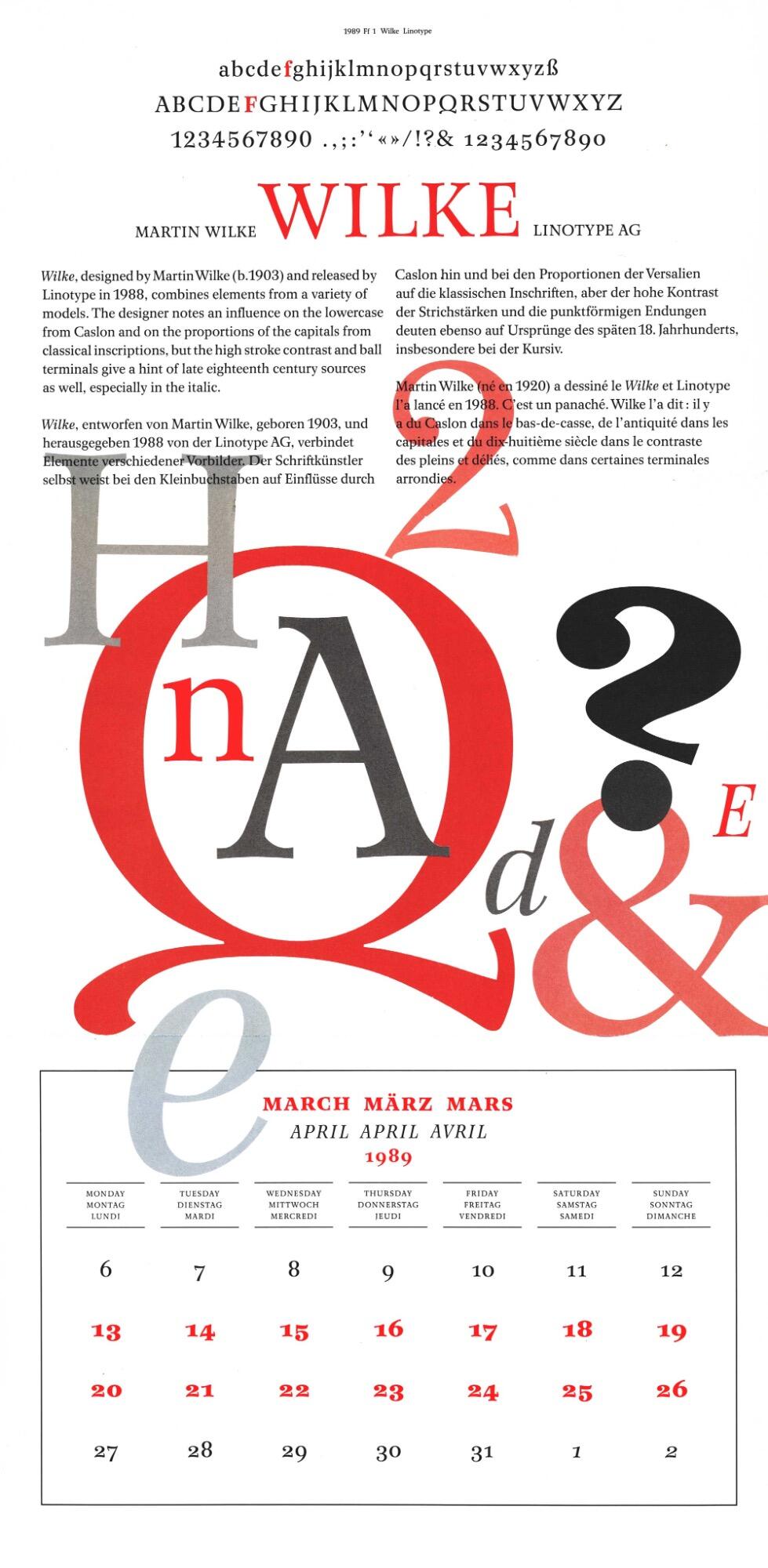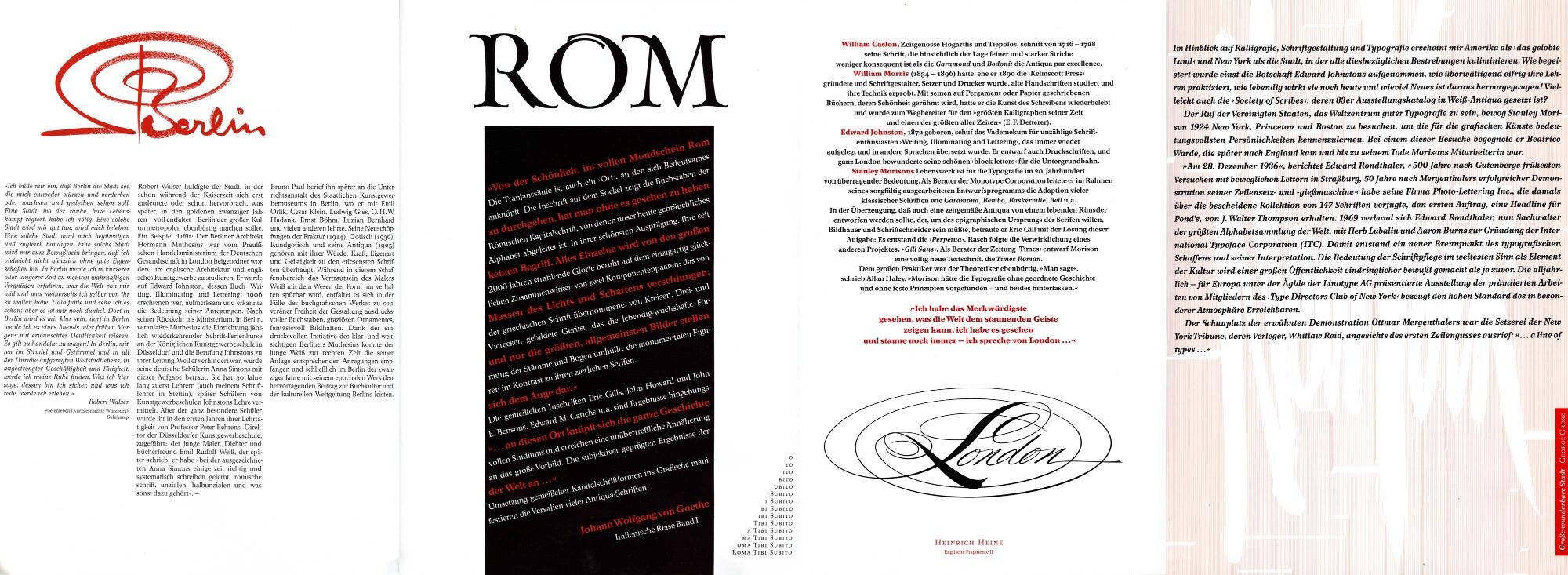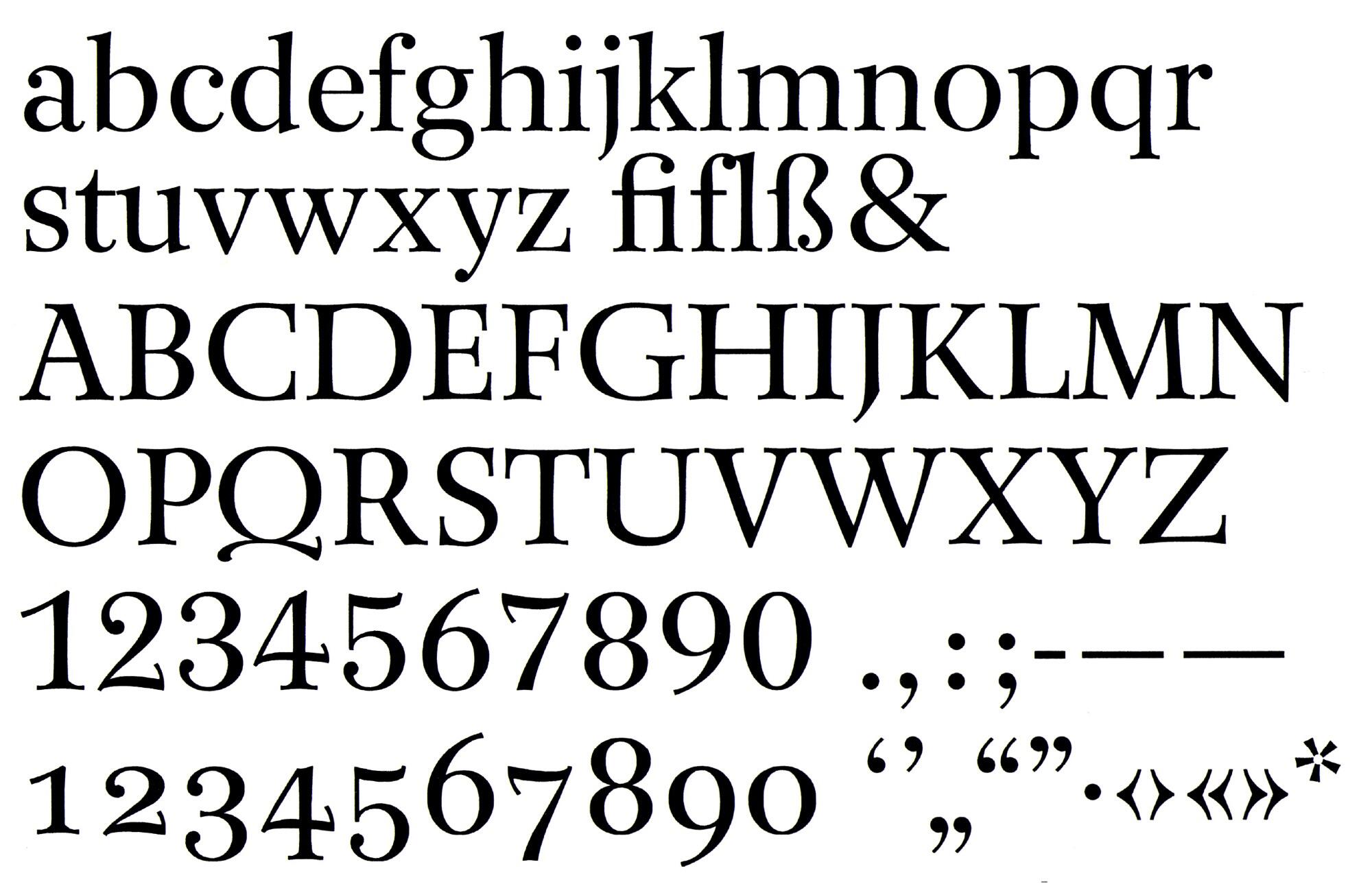
Die Wilke ist eine nach ihrem Gestalter Martin Wilke benannte Barock-Antiqua, 1988 herausgegeben von Linotype für den Fotosatz. In drei Schnitten mit Kursiven veröffentlicht, benannte Wilke die frührömische Capitalis Quadrata, die Kalligraphie des Book of Kells, Schriften Jan van de Veldes und die Caslon-Antiqua als Einflüsse.
Bei der Erstellung seiner letzten veröffentlichten Schrift setzte Martin Wilke auf organische Elemente für eine ›Schrift ohne Kühle und Strenge‹. Die Wilke hat eine leichte Vorwärtsneigung, alle Konturen sind leicht geschwungen, und außer bei den Querstrichen von A, f und t enthält sie keine geraden Linien.
Die digital über Monotype verfügbare Version enthält weder die ursprünglich vorhandenen Mediäval-Ziffern noch Kapitälchen.
Linotype Prospekt, Mittelseiten, 1988 (Martin Wilke & Ralf Rudorf)
Linotype Prospekt, Innenseiten, 1988 (Martin Wilke & Ralf Rudorf)
Linotype Prospekt, 1988, Vignette (Martin Wilke)
Wilke Kalenderblatt, aus ›26 Letters/Lettern/Lettres, An Annual and Calendar 1989‹